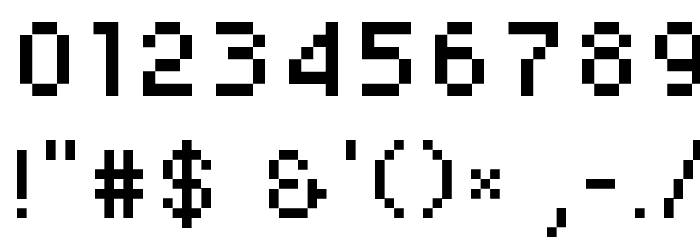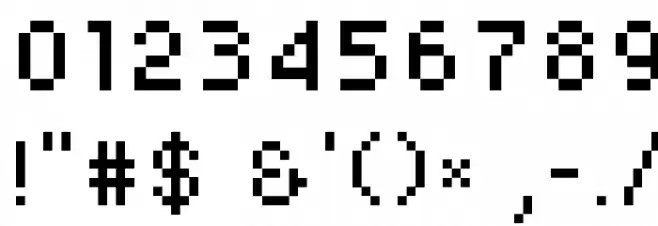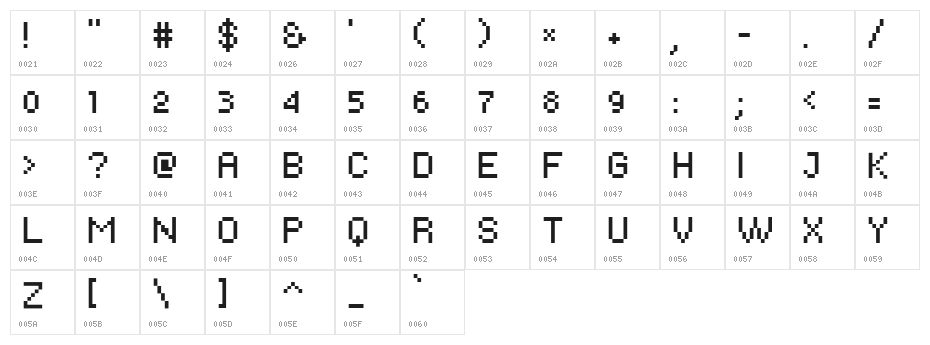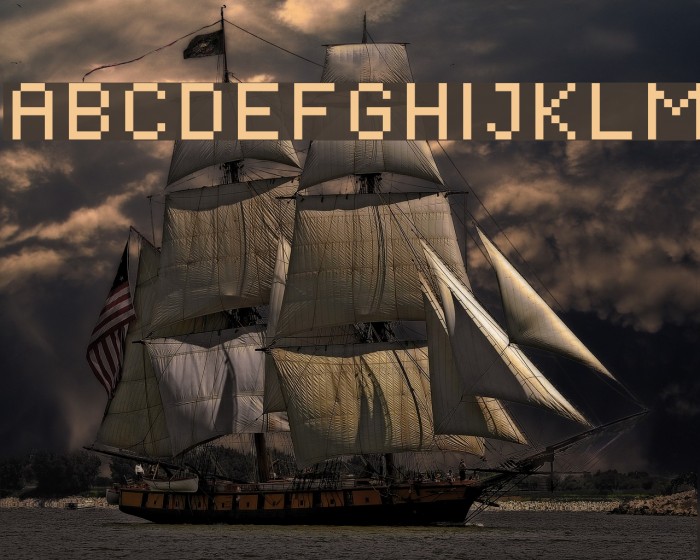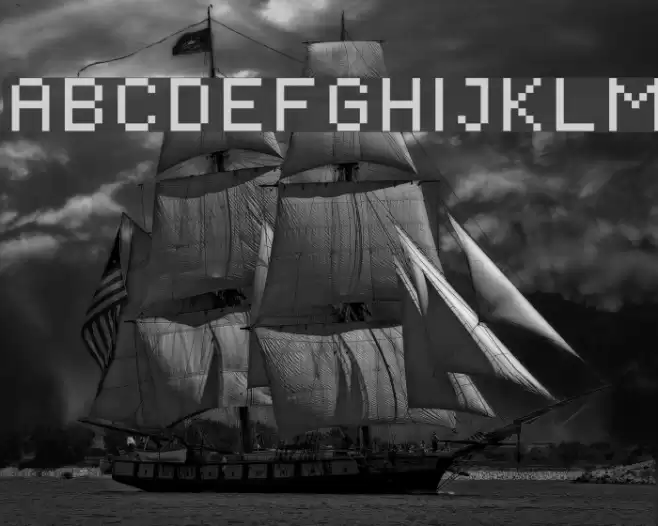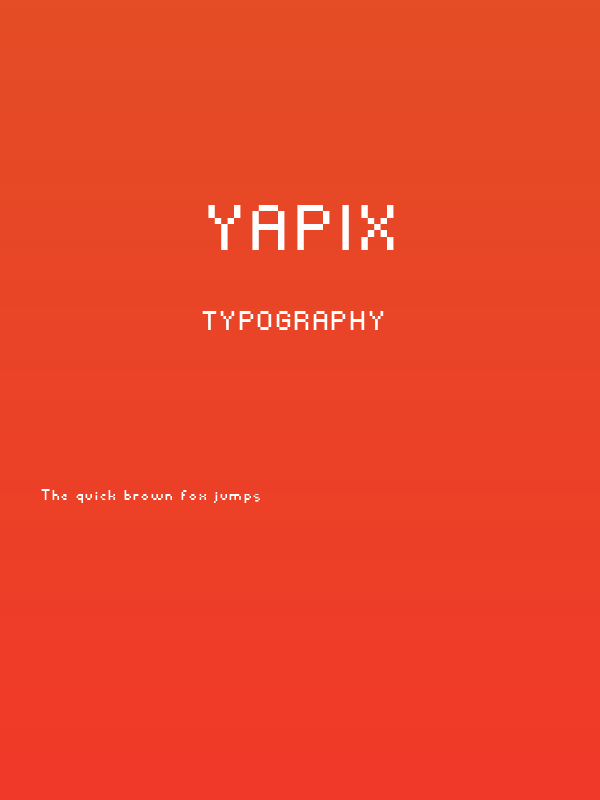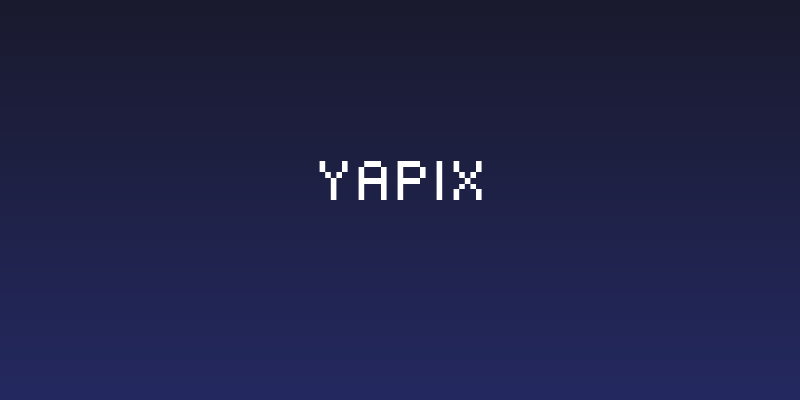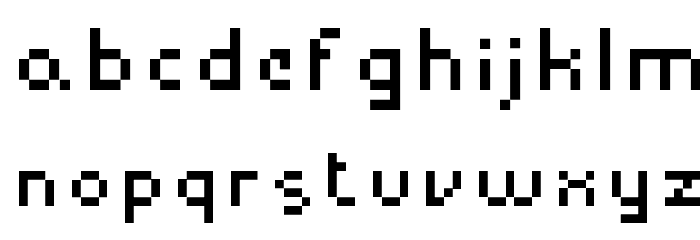
Yapix Font
| Stil general | Retro, Digital |
| Caz de utilizare | Logos, Headlines, Digital interfaces |
| Proiecte propuse | Ideal for retro video games, digital art projects, tech-themed posters, and websites. |